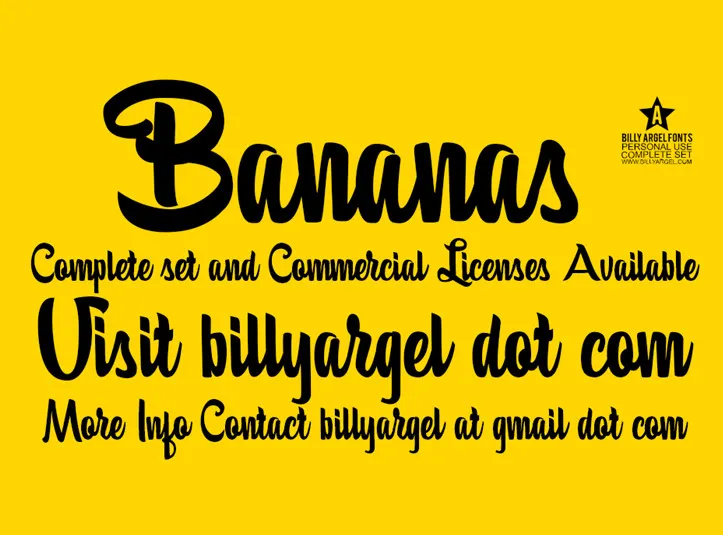
A fonte “Bananas Font” é uma delicada e elegante obra de arte tipográfica criada pelo designer Hamilton. Este conjunto particular e livre para uso pessoal se destaca por seu estilo alegre e descontraído, ideal para um toque divertido em qualquer projeto que você esteja desenvolvendo. Para quem busca incorporar uma personalidade única em suas criações, essa fonte não pode ser deixada de lado. Não é apenas sobre estética; “Bananas Font” também oferece a possibilidade de customização e flexibilidade nos seus projetos. A fonte vem disponível tanto para uso pessoal como para licenciamento comercial. Se você está considerando incorporá-la em um projeto maior, vale a pena pesquisar mais informações sobre o completo conjunto do designer no site billyargel.com. Hamilton é conhecido por criar designs únicos e divertidos que se conectam com os nossos sentidos, fazendo de “Bananas Font” uma escolha inteligente para quem valoriza criatividade e personalização. Visite o website da Billy Argel para explorar mais sobre suas outras fontes e design.